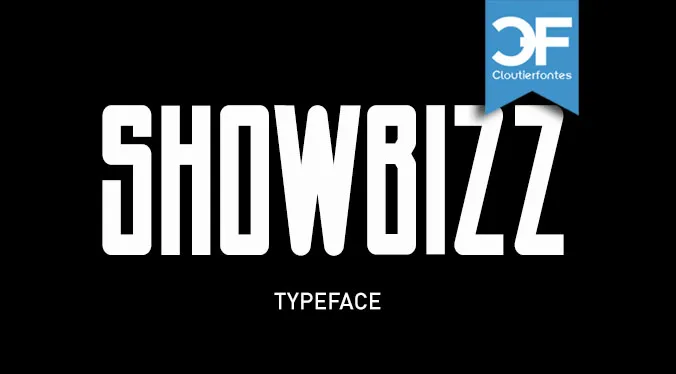
A Font CF Showbizz é uma elegante fonte sans-serif que traz alegria para qualquer projeto visual. Seu design clean e moderno foi criado pela CloutierFontes, oferecendo um equilíbrio perfeito entre funcionalidade e aparição fresca. Essa fonte não só combina bem com diversos estilos de design gráfico como também é adequada para títulos de texto grandes em postagens de blog ou artigos informativos. Para quem busca uma opção versátil, sem comprometer a presença visual, a CF Showbizz é uma escolha ótima. Se você está procurando por um estilo que seja o centro das atenções, este design oferece a flexibilidade necessária para destacar seu texto em qualquer plataforma digital ou impressa. A fonte tem sido projetada para criar um impacto visual atraente sem perder sua simplicidade e elegância. Se você está procurando por mais detalhes sobre como utilizar esta font na sua próxima publicação, visite a página web da CloutierFontes. Aqui encontrará informações úteis sobre licenciamentos e direitos autorais para garantir que você esteja sempre de acordo com as normas legais ao usar essa maravilhosa fonte CF Showbizz.